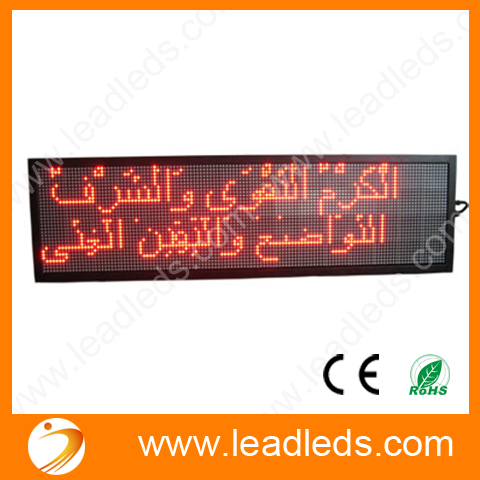
Frage zu Arabisch auf Bitmap-Basis
Hier mal eher eine Frage nicht so sehr zur Typografie an sich, sondern mehr zur Machbarkeit:
Wir haben vor einiger Zeit ein Kfz-Entertainment-System zunächst für den westlichen Markt entwickelt.
Es hat ein reines S/W-Display (Anti-Aliasing ist also nicht möglich) mit einer relativ geringen Auflösung von 78 px vertikal. Dort haben wir vier Zeilen Text untergebracht. Der Text basiert auf einem selbst gebauten Bitmap-Font. Die Buchstaben sind inkl. Ober- und Unterlänge 13 px hoch, der Zeilenabstand beträgt 16 px.
Jetzt fragt der Kunde Arabisch an.
Nun meine Fragen:
1. Ist Arabisch in einer so kleinen Auflösung ohne Graustufen/Anti-Aliasing überhaupt möglich?
Gibt es da irgendwelche Studien über Mindestgrößen?
2. Unser Framework hat zur Zeit keine TrueType-Unterstützung. Für den Fall, das Frage 1 mit Ja beantwortet werden kann: Welcher Ansatz hat mehr Aussicht auf Erfolg:
• TrueType Engine implementieren (oder zukaufen und integrieren) mit allen Modulen, die für das erfolgreiche Setzen von Arabisch notwendig sind (aber im Hinterkopf behalten, dass wir nur S/W in niedriger Auflösung können) oder
• versuchen, Arabisch auf Basis von Bitmap-Fonts zu implementieren?
Der zweite Ansatz klingt für mich eher kompliziert, da die gesamte Intelligenz, die in einer TrueType-Engine steckt bzgl. Zeichen verbinden usw., für Bitmaps nachgebaut werden muss.
Oder kennt jemand eine Kauf-Lösung auf Bitmap-Basis? Vermutlich hat es ja früher zu Zeiten eines Nokia 6310 auch schon arabische Low-Res-HMIs gegeben, die irgendwie funktioniert haben müssen.
eine schnelle Googelei: Das scheint mir 14 px hoch zu sein, geht also auch vierzeilig auf 78 px.
Wie gesagt: Bis jetzt benutzen wir für die westlichen Varianten zwei Bitmap-Fonts (13px und 18px inkl. Ober- und Unterlängen) mit je knapp 450 Zeichen, die wir extra für diesen Zweck haben anfertigen lassen. Ein dritter, "ausgegrauter" Font ist dadurch entstanden, dass man beim 13px-Font schachbrettartig jedes zweite Pixel weggelassen hat. Nicht wirklich schön, aber angesichts der Einschränkungen des Displays wohl nicht anders machbar.
Irgendwie habe ich die Hoffnung noch nicht ganz aufgegeben, dass man auch Arabisch mit Bitmaps in den Griff bekommt.
Ich kann mir nur schwer vorstellen, dass der Text auf dem Display, das Bertel im Internet gefunden hat, auf TrueType beruht. Aber vielleicht ist es dort auch kein dynamischer Text, so dass man die Wörter vorher als Grafiken rendern könnte …
Mein Halbwissen über Arabisch ist eher weniger als halb … Was ich ungefähr weiß, ist, dass jedes Zeichen in vier Ausprägungen daherkommt, je nachdem, ob es allein, am Anfang, in der Mitte oder am Ende eines Wortes steht. Weiterhin können aus zwei (oder mehr?) aufeinanderfolgende Zeichen Ligaturen entstehen. Mein Verständnis ist, dass diese Ligaturen obligatorisch sind, während sie z.B. im Deutschen meist nur nice-to-have sind (ffi – ffi). Man möge mich korrigieren.
Gibt es für diese Ligaturen Tabellen? So ähnlich wie Kerning-Tabellen, meine ich. Nach dem Motto: Was muss ich tun/wie muss ich korrigierend eingreifen, wenn ich bestimmte Zeichenkombinationen antreffe?
Monotype werde ich auf jeden Fall auch kontaktieren, zumal unser Kunde schon eine Liaison mit Monotype hat und ich auch schon Kontakt zu Mitarbeitern in England und Deutschland hatte. Mir kommt es nur so vor, dass die Implementierung einer TrueType-basierten Lösung für ein letztlich relativ niedrig auflösendes Dot-Matrix-Display vielleicht ein bisschen mit Kanonen auf Spatzen geschossen ist …
Und generell frage ich mich gerade, wie man ausgegrauten arabischen Text darstellen will, also ob das Arabisch noch lesbar ist, wenn man – wie bei den lateinischen Buchstaben – jedes zweite Pixel einfach weglässt. Vielleicht ist das in unserem Fall auch schon das Killerkriterium?!